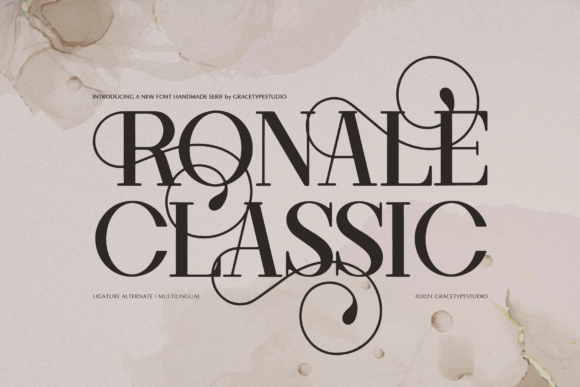
Ronale Classic
Ronale Classic : Une police serif handmade qui fait la différence
Si vous cherchez une police versatile et stylée pour donner du caractère à vos créations, Ronale Classic est faite pour vous. Conçue à la main, cette police serif associe le charme artisanal à une lisibilité moderne, ce qui la rend idéale pour une multitude de projets créatifs.
Pourquoi choisir Ronale Classic ?
- Style unique : Son aspect « handmade serif » apporte une touche d’authenticité qui se démarque sur les logos, les emballages et les supports imprimés.
- Polyvalence exceptionnelle : Parfait pour les logos, le branding, la décoration intérieure, les mugs, les citations, les affiches, les sacs, les t‑shirts, les couvertures de livre, les cartes de visite, les invitations, les cartes de vœux, les étiquettes, les filigranes photo, et même la planification d’événements.
- Caractères PUA encodés : Tous les glyphes spéciaux sont intégrés directement dans la police, ce qui élimine le besoin de logiciels de conception supplémentaires.
Applications concrètes de Ronale Classic
Voici quelques idées inspirantes pour exploiter le plein potentiel de cette police :
- Création de logos mémorables pour des marques artisanales ou vintage.
- Design d'emballages produits (boîtes, étiquettes, sacs) qui attirent le regard en rayon.
- Réalisation d'affiches et de posters pour des événements culturels ou des campagnes publicitaires.
- Personnalisation de t‑shirts et de mugs avec des citations typographiques.
- Conception de cartes d’invitation et de cartes de vœux au style élégant et chaleureux.
- Ajout de filigranes uniques à vos photographies professionnelles.
Verdict final
Ronale Classic se démarque comme une police serif handmade indispensable pour les créatifs qui veulent mêler authenticité et modernité. Sa large gamme d’applications, son encodage PUA complet et sa gratuité en font un choix judicieux pour tout projet de design, du plus simple au plus ambitieux.